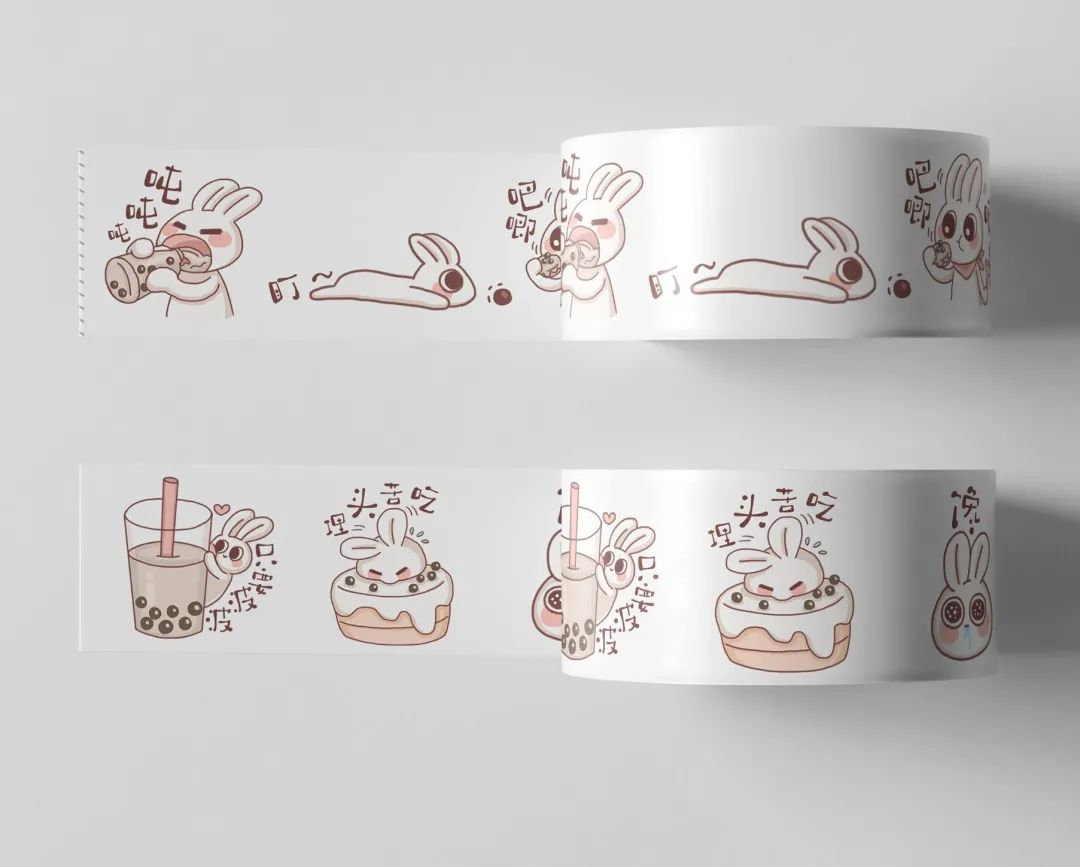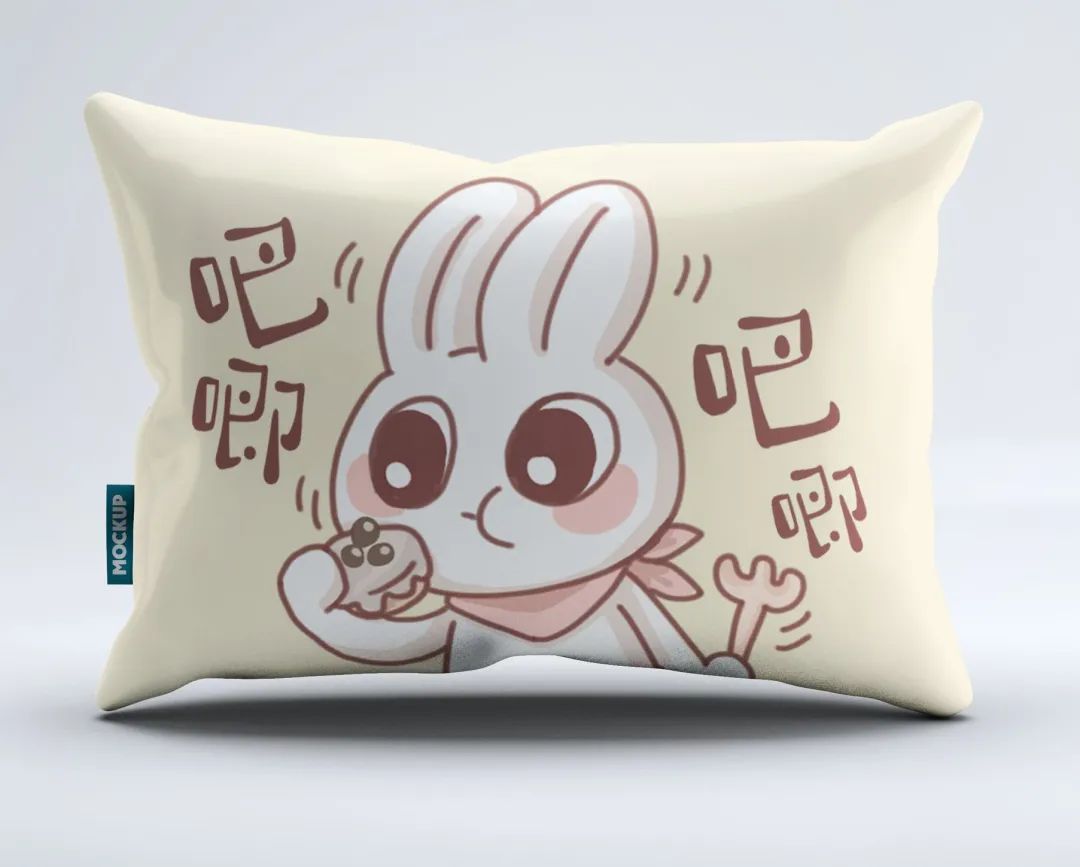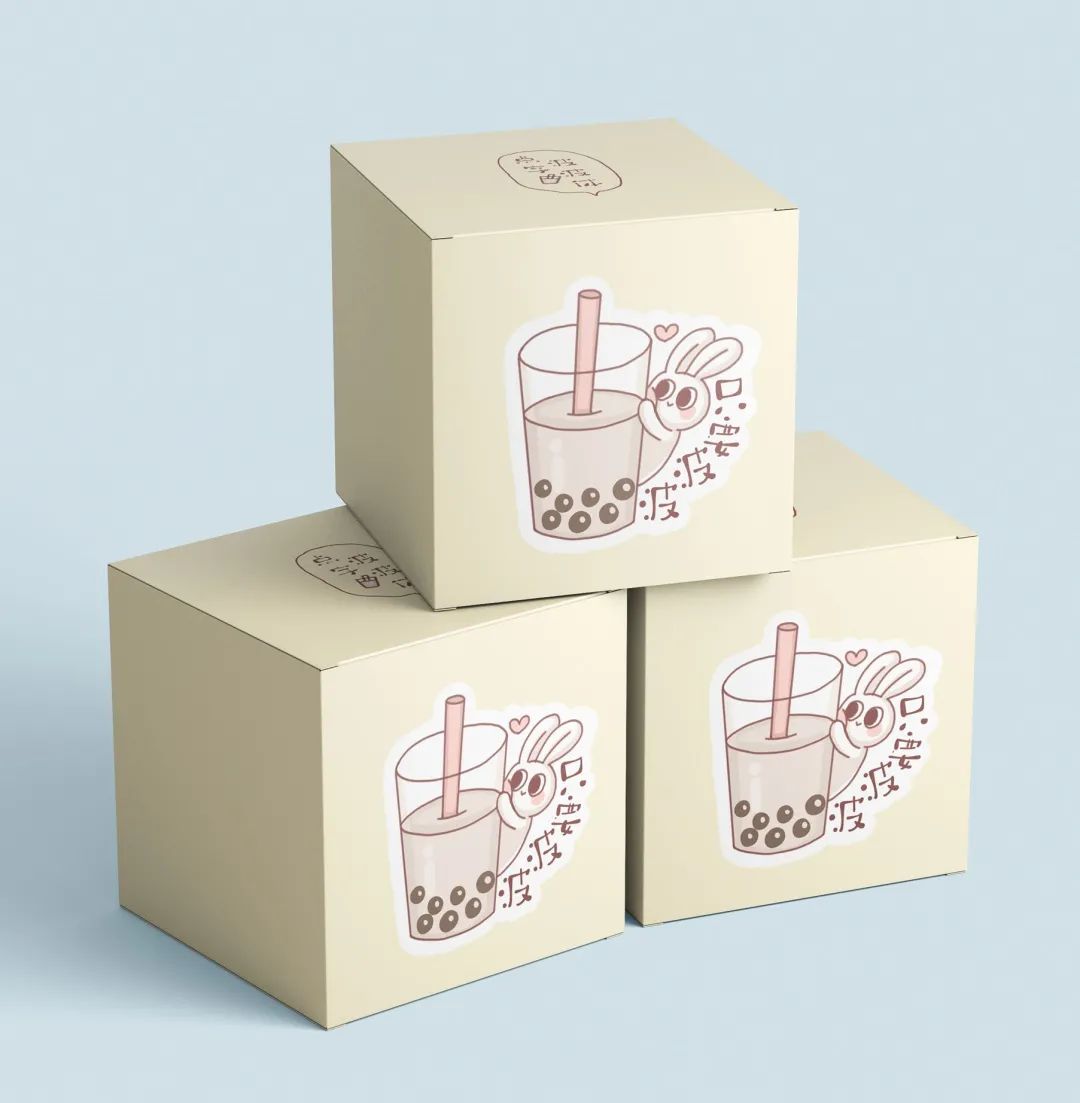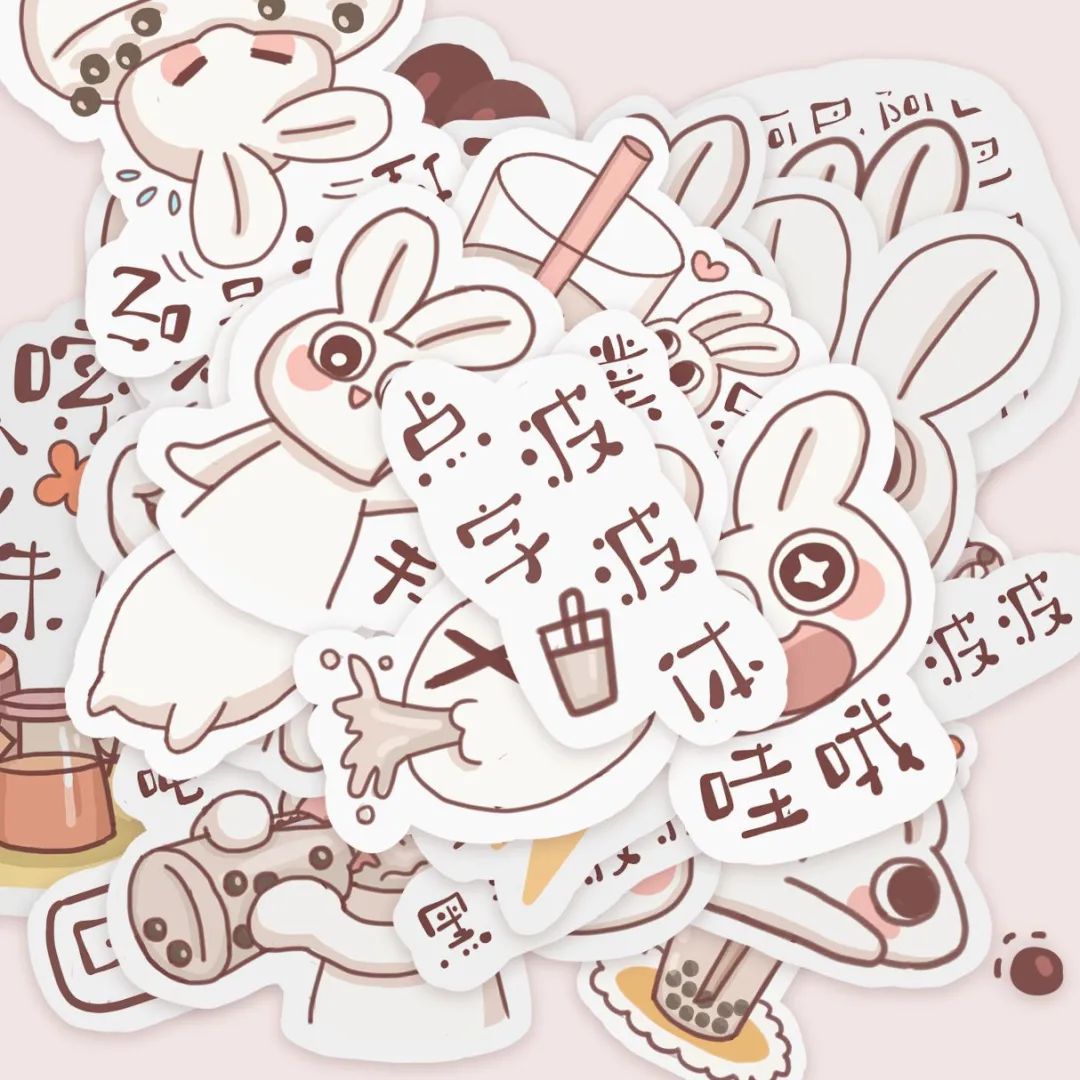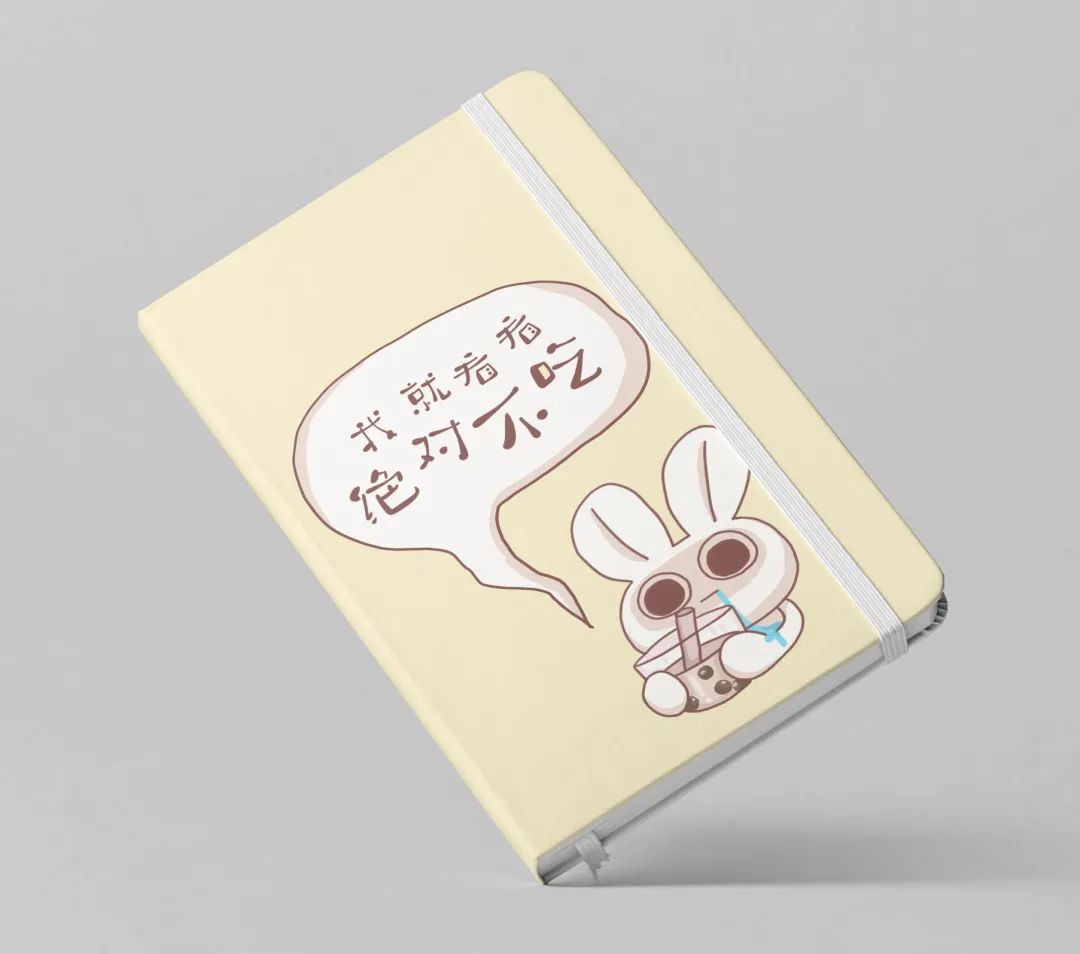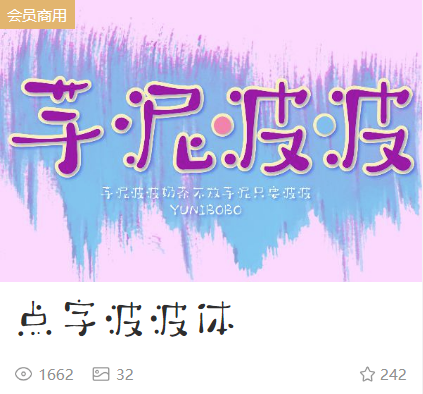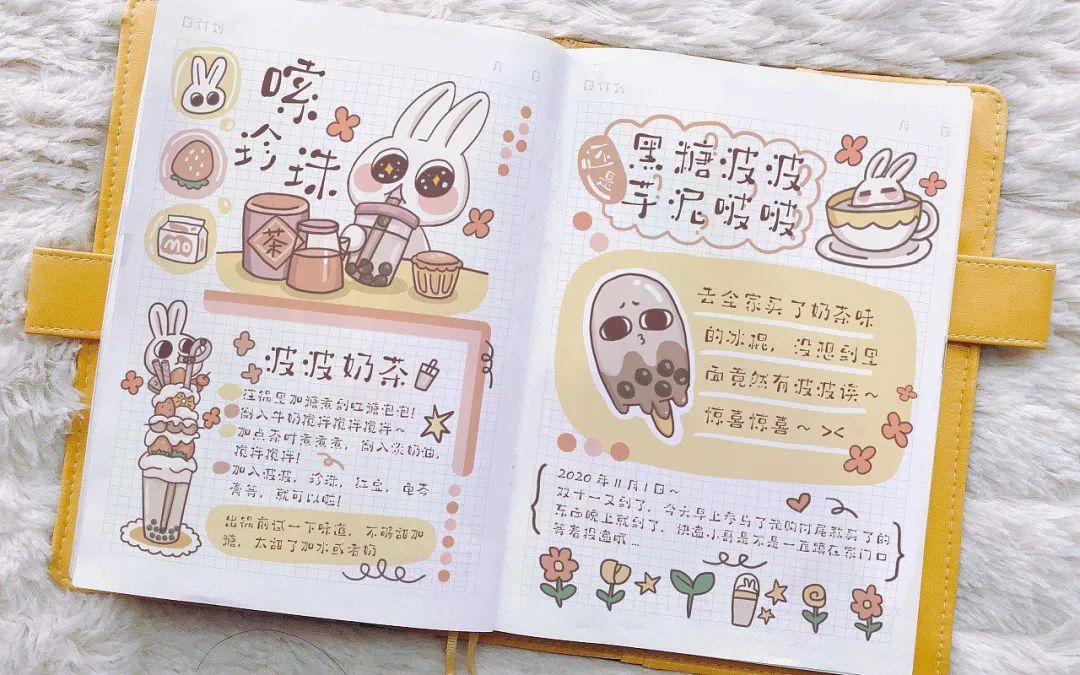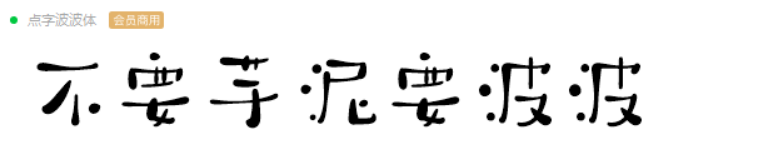
点字波波体字体介绍,一个平平无奇的喝奶茶小天才~
Hi,我是波波兔,我有一个绝技,那就是每天可以变着花样吃ˉ﹃ˉ
但不加节制的后果就是,我成了一个肥肥兔。
肿么办,要减肥了,先定一个小目标。
但看到最爱的奶茶,又放弃了 >﹏<
你问我为何这么欲罢不能?因为我喜欢……
就算遇到了最爱的芋泥波波奶茶,也只要波波~
看到波波,就会两眼放光^o^
甚至达到了望“波”止渴的地步。
你是不是也跟我一样,有这个甜蜜的烦恼?
那就换一种方式爱波波吧~
它圆润Q弹的手写笔触,就像奶茶一样,给人一种温暖有趣的感觉。
你可以把它用在很多可爱的周边中,一看就挪不开眼。